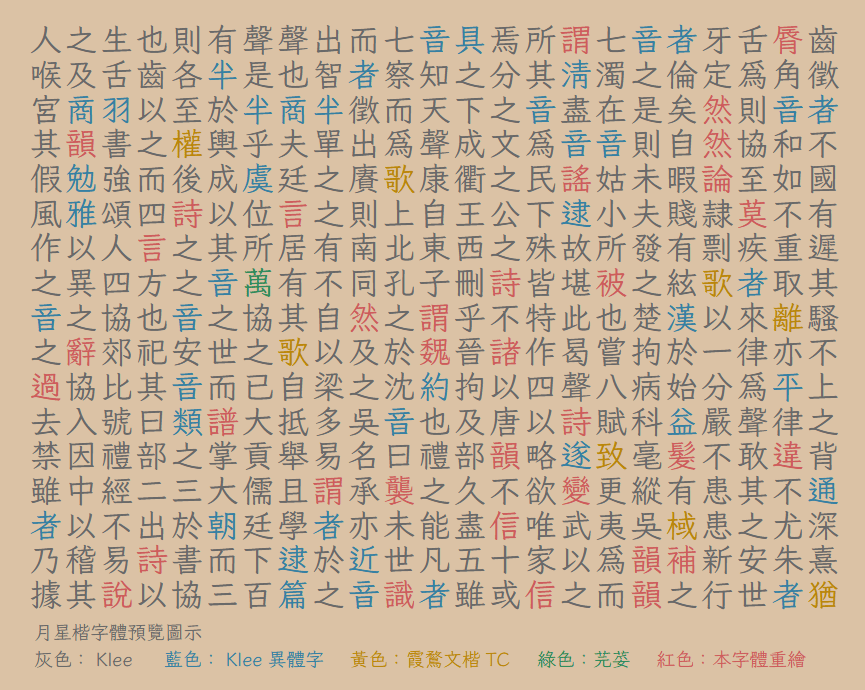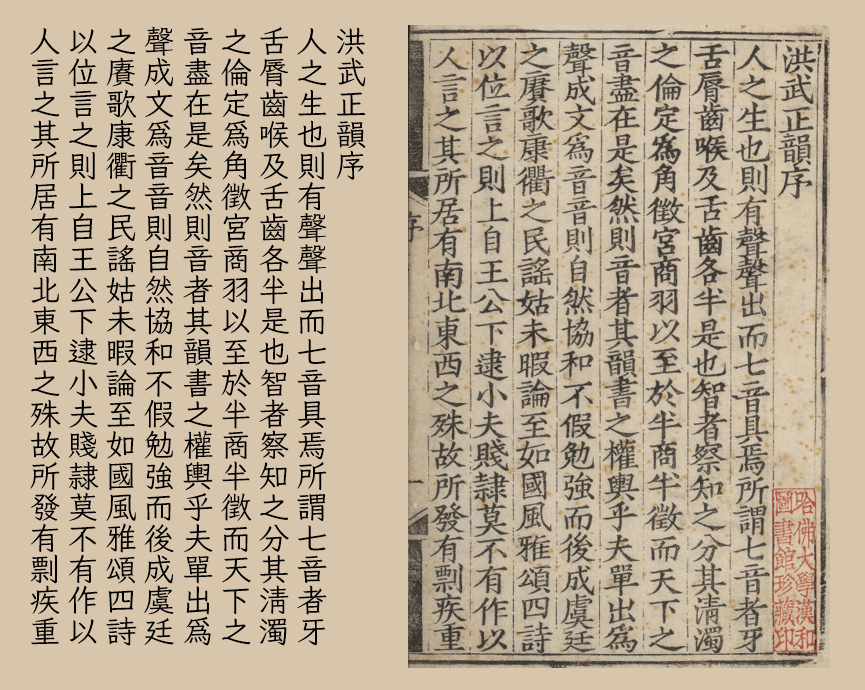
一款由 Klee 衍生旧字形或古体字形风格的中文字体。
Moon Stars Kai 月星楷
在 Klee One 的基础上,结合霞鹜文楷 TC、霞鹜文楷以及芫荽字形,参照《洪武正韵》(明嘉靖四十年刘以节刊本)制作。部分字形在现代书写中已经很少见,但可常见于书法字贴。
Moon Stars Kai T 月星楷 繁
由月星楷修改,简入繁出的字体。此字体使用了 OpenType 功能,可根据文本内容动态匹配一简多繁的情况。